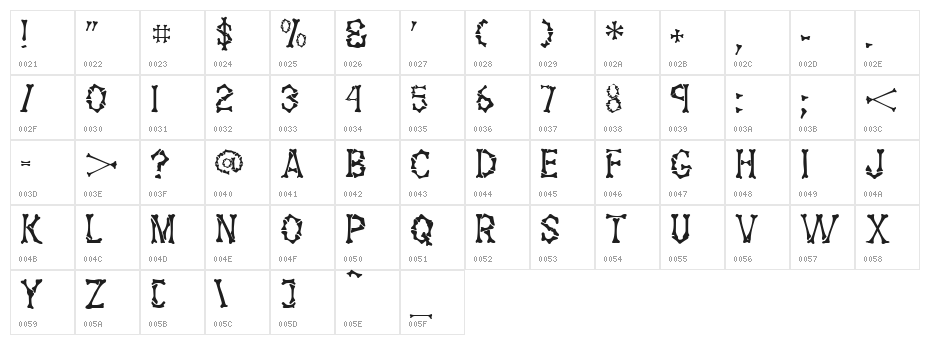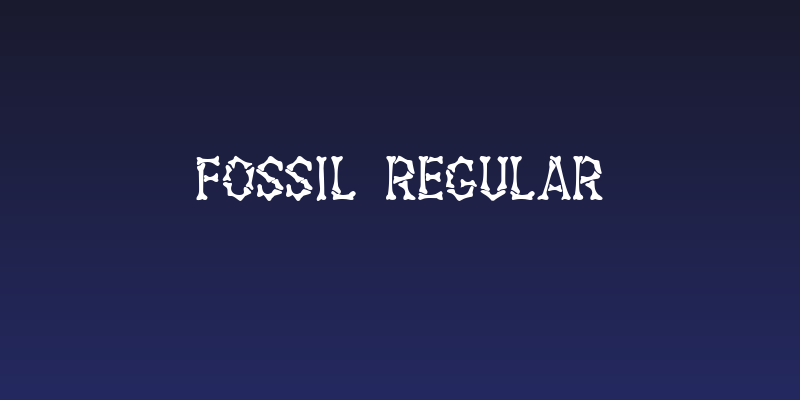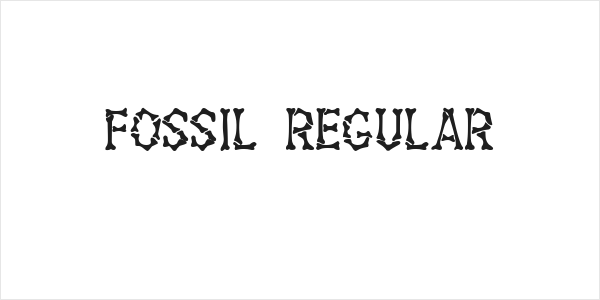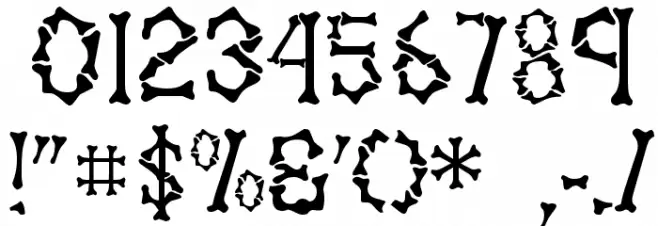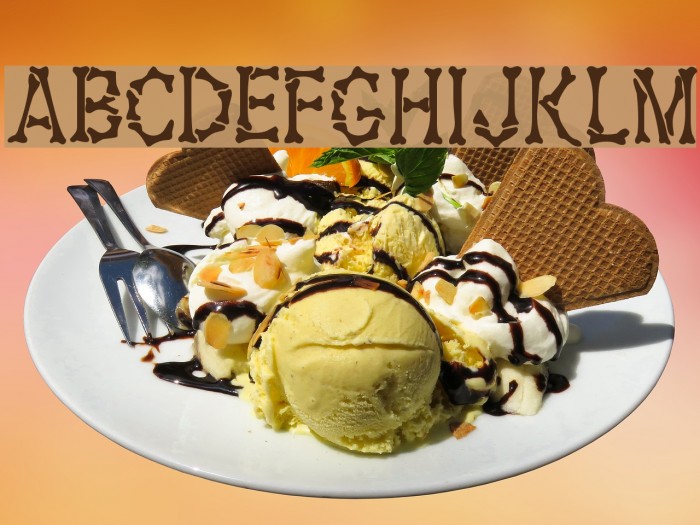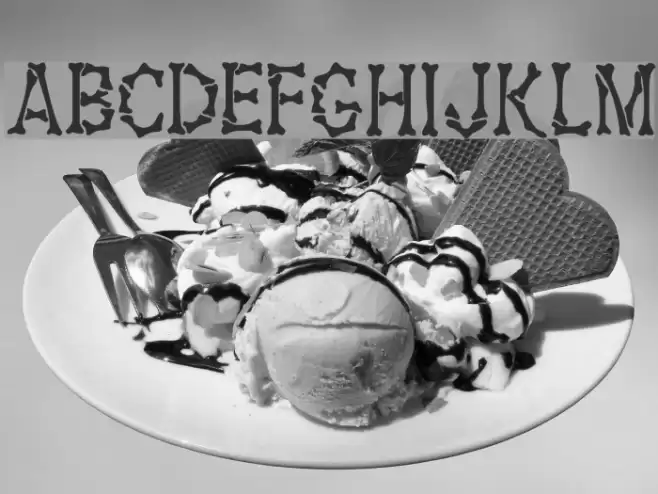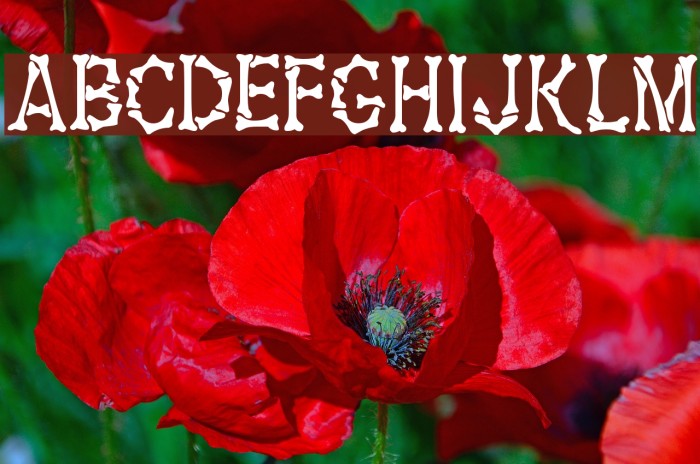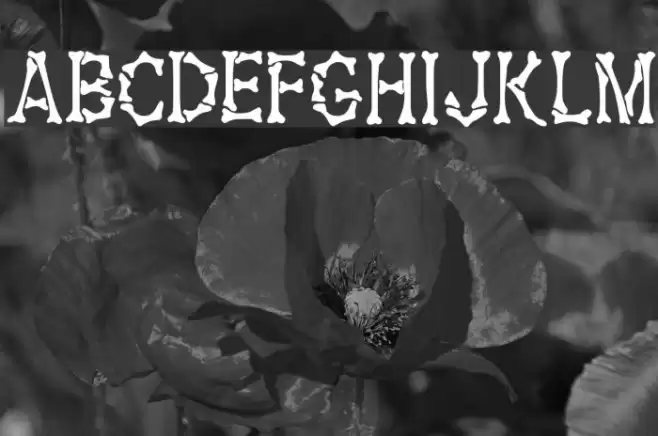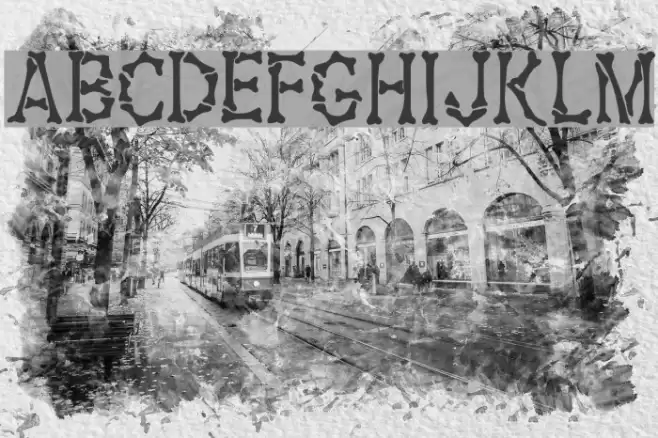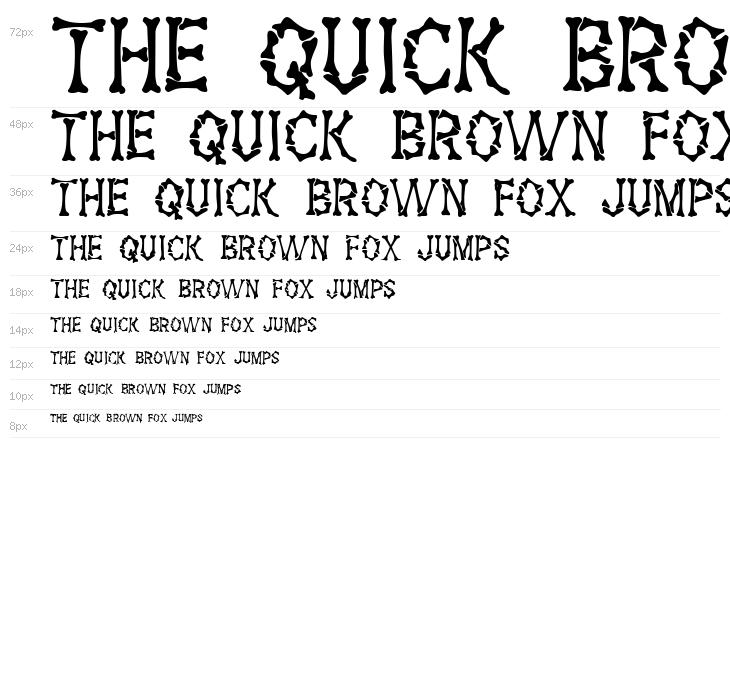
Fossil Regular Font
| Cas d'utilisation | Headlines, Logos, Themed Events |
| Projets proposés | Ideal for dinosaur-themed events, adventure park branding, educational materials on paleontology, or any project seeking a prehistoric vibe. |